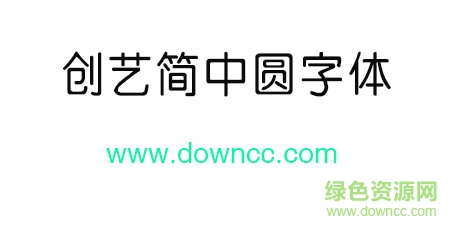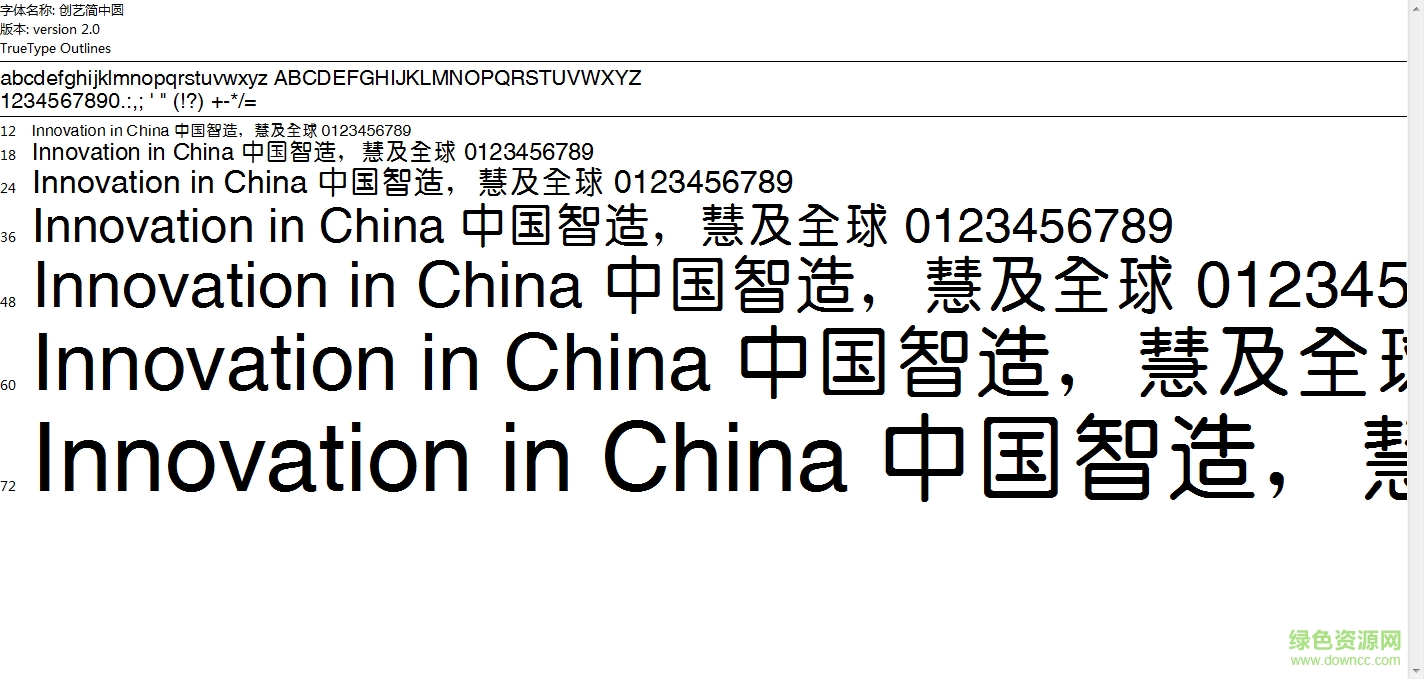
ctzhongyuansj字體就是創(chuàng)藝簡中圓字體,該字體筆觸細膩,字形簡潔優(yōu)雅,十分美觀,讓你在創(chuàng)作文章時都會有一項更好的字體選擇,而且還是可以永久免費使用的哦。你可千萬別錯過了,喜歡的小伙伴快來綠色資源網(wǎng)下載收藏吧!
創(chuàng)藝簡中圓是一款簡單、大方的簡體廣告字體,創(chuàng)藝簡細圓字體筆畫均衡,折角處圓潤沒有棱角。如果你想將其用于商業(yè)用途,則需要聯(lián)系作者取得授權(quán)。
筆畫適中,造型秀美適意,筆畫流暢,點畫呼應(yīng),用在很小的字號時仍具有清晰、明快的閱讀效果~!